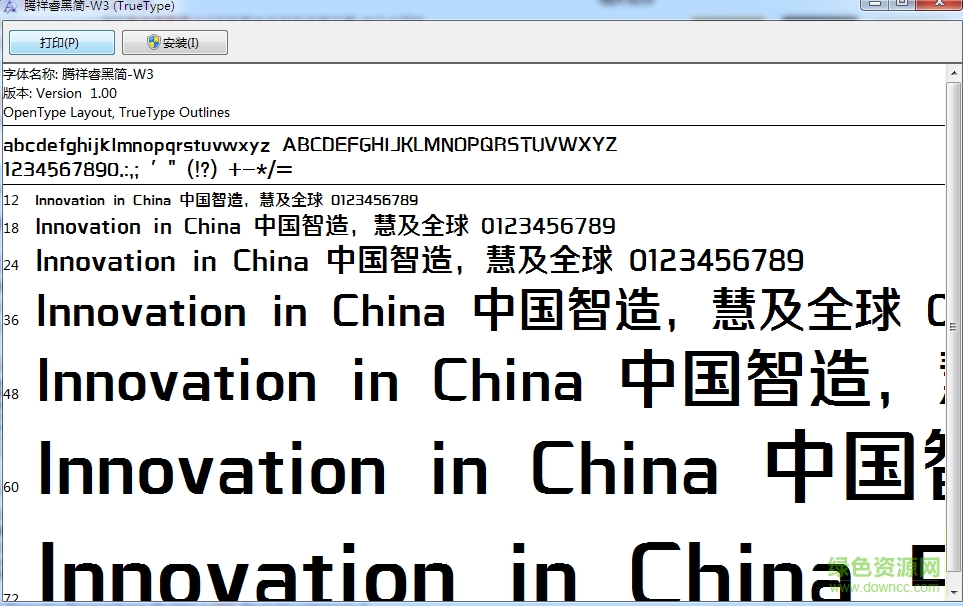
騰祥睿黑簡W3字體是一款黑體風(fēng)格的電腦字體,字形結(jié)構(gòu)方正、端莊,橫豎筆畫挺拔,軟筆畫細(xì)膩、柔美。黑白均勻、行文貫通,可用于各種設(shè)計(jì)場合,喜歡就來綠色資源網(wǎng)下載吧!
騰祥睿黑-W3為騰祥睿黑系列字庫是騰祥公司自主精心設(shè)計(jì)開發(fā)的黑體字體,不管是常用字或是非常用字,字字精美、結(jié)構(gòu)端正、重心平穩(wěn)、美觀實(shí)用,適用于標(biāo)題、小標(biāo)題、正文、屏顯等。